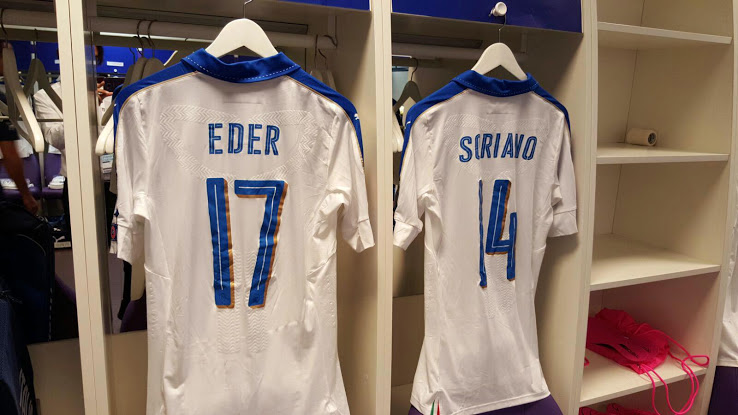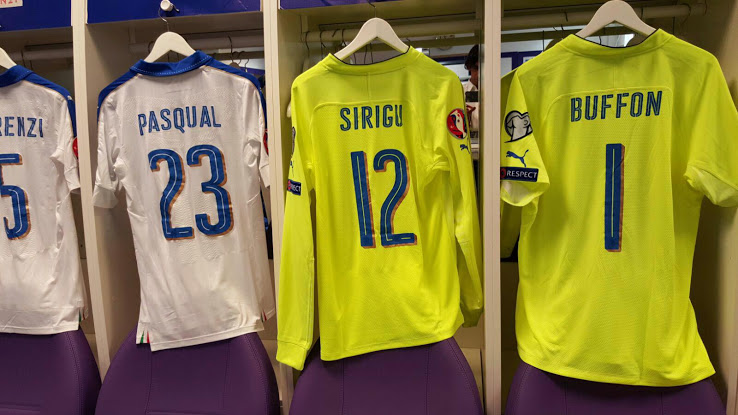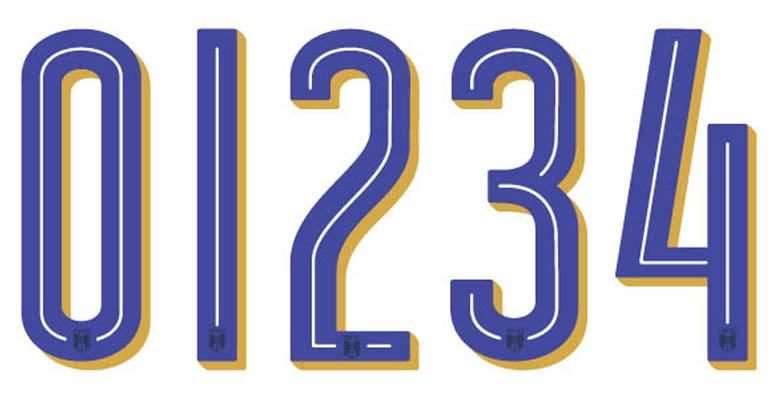
Italien EM 2016 Schriftart enthüllt
Puma hat - passend zum frühen Launch des Italien EM 2016 Auswärtstrikots - eine neue Schriftart für Spielernamen und -nummern entworfen. Dieselbe Schriftart wird auch für das Italien 2016 Heimtrikot verwendet, das im November veröffentlicht wird.
Italien war letzten September das erste Team, das sein EM 2016 Auswärtstrikot enthüllt hat und das neue Puma Italien EM 2016 Auswärtstrikot bereits im EM 2016 Qualifikationsspiel gegen Malta debütiert.
Italien EM 2016 Trikot-Schriftart
Das ist die neue Schriftart für Spielernamen und -nummern auf den Italien EM 2016 Trikots.
Die Italien EM 2016 Schriftart, die kaum auf Pumas vorherigen Arbeiten basiert, ist blau mit einem kontrastierenden goldenen Schatten, der vom Farbschema des Italien 2016 Auswärtstrikots inspiriert wurde.
Die Italien EM 2016 Schriftart kommt innerhalb jeder Nummer und jedes Buchstabens mit einer weißen Linie sowie einem einfarbigen Verbandswappen am unteren Ende der Nummern - ein wiederkehrendes Thema bei neuesten Trikot-Schriftarten.